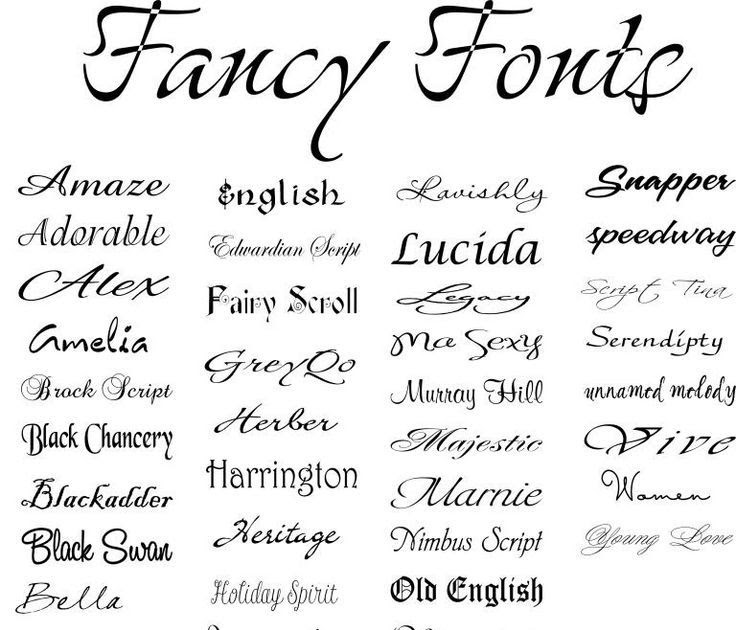
Элегантные шрифты. к генерировать разные источники для Instagram откройте платформу, напишите или вставьте свой текст, просмотрите его в разных стилях, скопируйте отрывок с нужным шрифтом и вставьте текст в Instagram, Facebook, Twitter, Youtube, WhatsApp, Twitch, TikTok или любая социальная сеть. Есть и другие места, которые также предлагают эту услугу.
Поскольку Instagram Stories предлагает определенные возможности, когда мы пишем описания, комментарии или сообщения, нет возможности, кроме шрифта по умолчанию.
Несмотря на это, есть сторонние инструменты которые предлагают пользователям возможность размещать другие источники. Продолжайте с нами, чтобы узнать больше об этой альтернативе и узнать, как используйте шрифты, которые делают ваши публикации более привлекательными, в данном случае элегантные шрифты.
Элегантные шрифты. Если вам нужно больше альтернатив для декорированного текста, просто нажмите «загрузить больше шрифтов». Варианты, которые появляются здесь, более случайны, немного отходят от стандарта и объединяют ресурсы, которые имеют мало общего, смайлики и символы.
Отличие сайта в том, что на нем есть функция для создания самого шрифта. Щелкнув «Создай свой собственный шрифт», вы можете выбрать символы, которые будут соответствовать каждой букве алфавита.
Instagram и другие социальные сети создают шрифт, который лучше всего адаптируется к общему формату системы. Это часть согласованности, необходимой для визуальной простоты навигации по этим приложениям.
— Элегантные шрифты. Оказывается, есть способ добавить стилизованные буквы, которые на самом деле являются специальными символами, а также смайлики и другие символы.
На практике они выглядят как пользовательские шрифты, но технически называются Символы Юникода.
Поэтому некоторые классные инструменты для этих шрифтов в Instagram можно настроить биографию профиля или выделите части подписей к фотографиям и видео, которые вы публикуете. Это творческие способы улучшить вашу стратегию цифрового маркетинга.
Помня, что эти источники следует использовать экономно, в основном для
Какими бы забавными они ни были, чрезмерное их использование может создать впечатление, что ваша учетная запись слишком случайна.
Но используйте шрифты индивидуально сбалансированный стандартный шрифт — это нормально, если они разборчивы и эстетически соответствуют вашему бренду Кстати, это очень важно для тех, кто использует Instagram в компаниях или влиятельных лицах.
Поэтому выберите отрывок с тем шрифтом, который вы хотите использовать, и используйте команду копирования на вашем устройстве.
4. Instagram, Facebook, Twitter, Youtube, WhatsApp, Twitch, TikTok или любая социальная сеть.
Теперь, когда ваш текст сохранен в буфере обмена вашего ПК или телефона, используйте команду
Элегантные шрифты. Помните, что может возникнуть некоторая несовместимость символов Unicode. Следовательно, убедитесь, что фрагмент отображается так, как ожидалось И если да, отрегулируйте его, чтобы не удивлять своих подписчиков.
Наконец, мы рекомендуем вам выбрать один или два из этих шрифтов для частого использования, чтобы они особенность ваших сообщений.
Поэтому попробуйте использовать шрифты, чтобы улучшить внешний вид субтитров, которые вы пишете для изображений.
И не забывай используйте стилизованные буквы в биографии профиля, если вы сочтете это актуальным. Используйте эту функцию, чтобы привлечь тех, кто еще не подписан, а также побудить тех, кто уже подписан на вас, предпринять определенные действия.
Вам понравились наши советы по шрифтам для социальных сетей?
Легкие шрифты для ваших сообщений
После быстрой обработки без труда публикуйте оригинальные шрифты, которые становятся цифровые шедевры и получают тысячи лайков.
Однако, если вы не являетесь опытным художником-графиком и специальное программное обеспечение не является вашей сильной стороной, попробуйте наш инструмент. Это современный конструктор, с помощью которого вы увеличите охват в социальных сетях.
FRUTILLA
Каллиграфический шрифт не обязательно должен быть классическим, чтобы быть элегантным. Рукописные шрифты в современном стиле также красивы и элегантны. Frutilla, разработанный Яном Микразом, идеально подходит для Instagram, сайтов о женском образе жизни и элегантных свадебных приглашений в современном стиле.